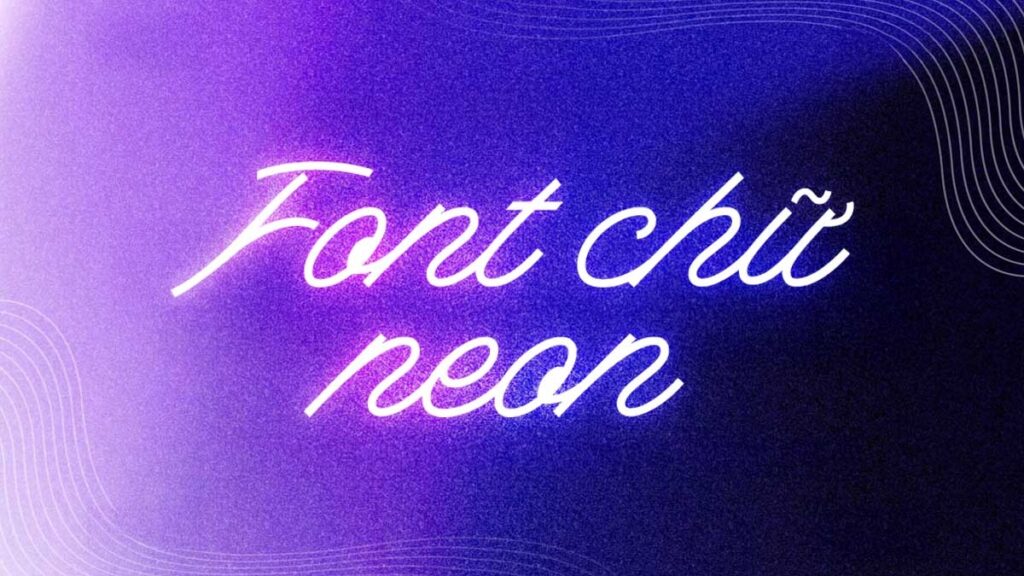
Font chữ led neon là nhóm phông chữ đặc thù được thiết kế dựa trên kỹ thuật uốn ống thủy tinh và dây LED neon flex dẻo, nổi bật với cấu trúc nét đơn liền mạch, các góc bo tròn mềm mại và không có điểm gấp khúc quá gắt. Với khả năng mô phỏng sinh động ánh sáng phát quang rực rỡ trong đêm, font chữ đèn led neon là chất liệu trực quan tuyệt vời để các kiến trúc sư, nhà thiết kế thổi hồn vào các bản vẽ phối cảnh quầy bar container, góc check-in homestay giới trẻ hay biển hiệu mặt tiền quán cà phê phố.
Đường nét uốn ống liền mạch và hiệu ứng phát quang của font chữ led neon
Điểm cuốn hút của font chữ led neon nằm ở độ dày nét chữ hoàn toàn đồng nhất từ đầu đến cuối, mô phỏng chính xác đường kính thực tế của các loại dây LED silicone hiện đại. Cấu trúc chữ sở hữu những đường cong lượn sóng tự nhiên, các điểm nối giữa các ký tự được tính toán để dòng điện ánh sáng như chảy tràn liên tục trên bề mặt biển hiệu.
Sự ổn định về mặt thị giác của dòng font này giúp khơi gợi cảm xúc hào hứng, phong cách sống về đêm và năng lượng lễ hội sôi động. Khi xuất hiện trên các bề mặt vật liệu kiến trúc như vách tôn container sơn màu xám chì, tường cây nhân tạo, khung lưới sắt hay kính mờ trong các căn nhà lắp ghép nghỉ dưỡng, font chữ đèn neon tạo nên điểm nhấn ánh sáng hút mắt.
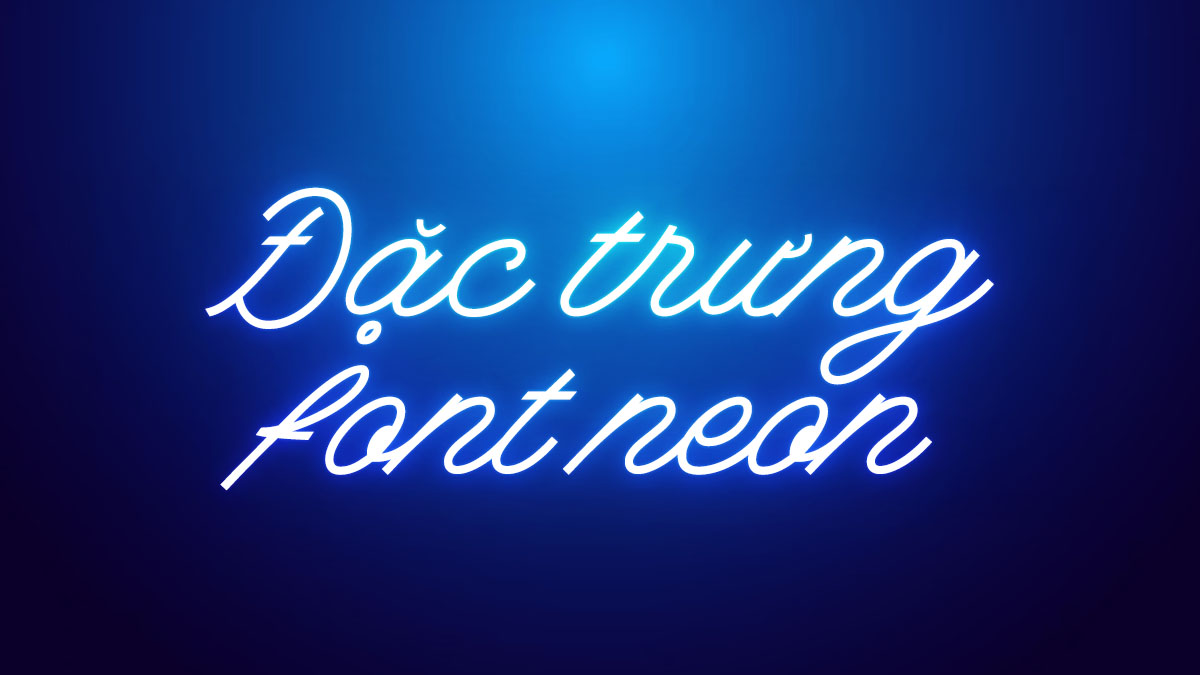
Tư vấn từ chuyên viên: Khi lựa chọn font chữ làm led neon, bạn nên ưu tiên các bộ phông có nét chữ liền mạch và bán kính góc cong lớn hơn 15mm. Điều này sẽ giúp người thợ thi công dễ dàng luồn dây LED dẻo vào rãnh mica mà không làm gãy gập mạch điện, giúp ánh sáng đèn tỏa đều và tăng tuổi thọ sử dụng cho biển hiệu.
03 Ứng dụng phông chữ đèn neon vào công trình thực tế
Nhờ vẻ ngoài rực rỡ và tính kết nối cao với kỹ thuật chiếu sáng hiện đại, bộ phông chữ này mang lại giá trị thực tế lớn trong khâu hoàn thiện các không gian giải trí:
- Biển hiệu mặt tiền và Bảng Menu Quán Bar Container: Những nét chữ uốn lượn phát sáng rực rỡ của font chữ làm đèn led neon rất ăn ý khi gắn trên vách tôn sóng màu đen mờ, mang lại diện mạo thời thượng, thu hút giới trẻ ghé thăm check-in và thưởng thức đồ uống.
- Góc chụp ảnh kỷ niệm cho Homestay: Phông chữ này khi uốn trên tấm mica trong suốt gắn tường cỏ nhân tạo sẽ tạo nên góc sống ảo lung linh, giúp du khách lưu lại những khoảnh khắc đáng nhớ trong kỳ nghỉ tại nhà lắp ghép.
- Trang trí không gian phòng ngủ và Sảnh đón tiếp văn phòng: Bạn có thể dùng phông chữ này để làm các câu trích dẫn truyền cảm hứng với ánh sáng vàng ấm hoặc hồng pastel, tạo cảm giác thư giãn và làm dịu đi sự thô cứng của các khối kim loại xây dựng.
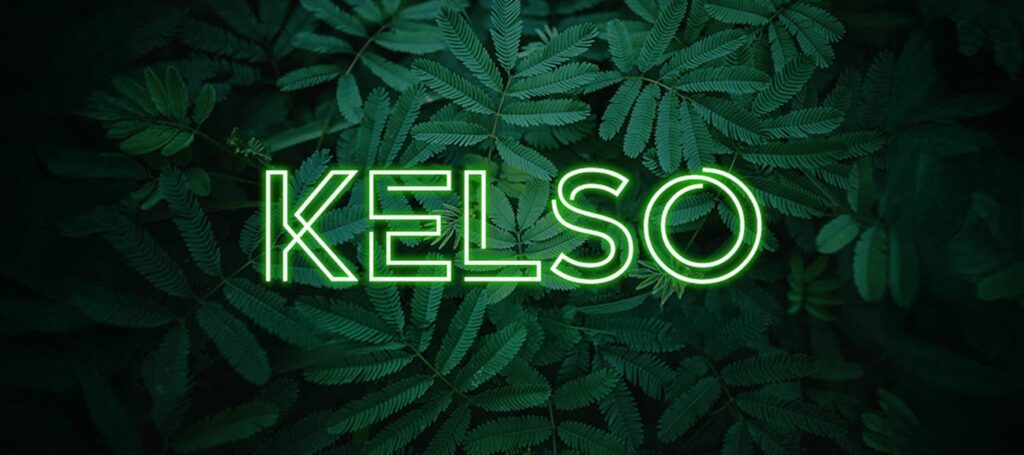
03 Lưu ý bố cục font chữ làm led neon thuận tiện cho gia công uốn dây
Để bản vẽ thiết kế chuyển đổi sang sản phẩm gia công cơ khí thực tế đạt độ hoàn thiện cao, người thiết kế nên lưu tâm một số kinh nghiệm sau:
- Tránh các góc bẻ quá gắt: Dây LED silicone có giới hạn về bán kính uốn cong. Khi sử dụng font chữ làm led neon, bạn nên hạn chế các góc nhọn dưới 60 độ để tránh tình trạng dây đèn bị nghẽn mạch hoặc bung mí dán khi thi công.
- Tối ưu hóa đường chạy dây: Ưu tiên chọn các kiểu chữ thảo có các nét nối liền mạch giữa các ký tự để giảm thiểu số lượng mối nối dây điện ẩn sau tấm nền mica, giúp biển hiệu có độ thẩm mỹ cao hơn khi nhìn gần.
- Lựa chọn gam màu phát quang tương phản: Phông chữ phát huy hiệu quả thị giác cao khi phối cùng các hiệu ứng viền sáng (Outer Glow) màu hồng neon, xanh ngọc bích, vàng nắng hoặc đỏ tươi trên nền vách sẫm màu, mô phỏng ánh sáng đèn đêm rực rỡ.